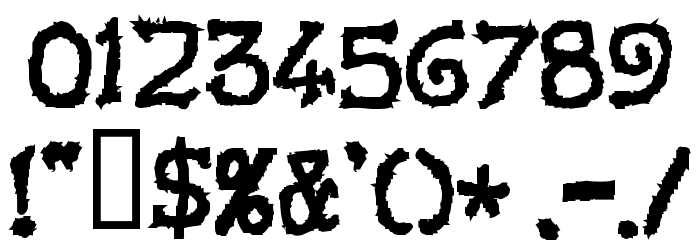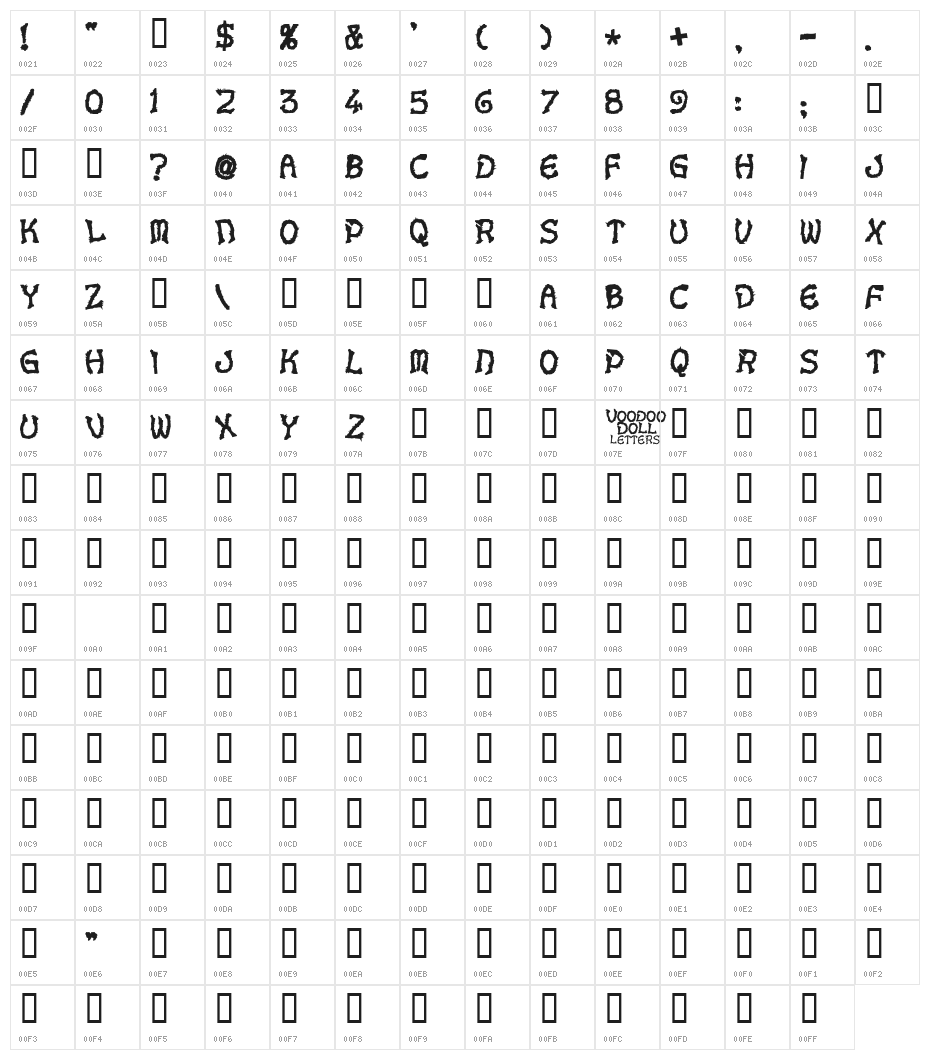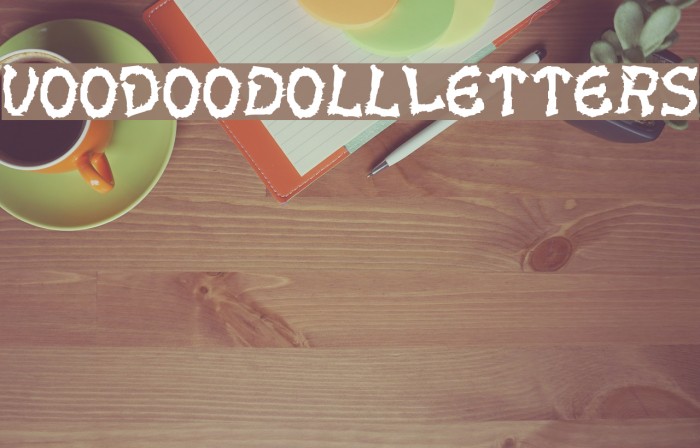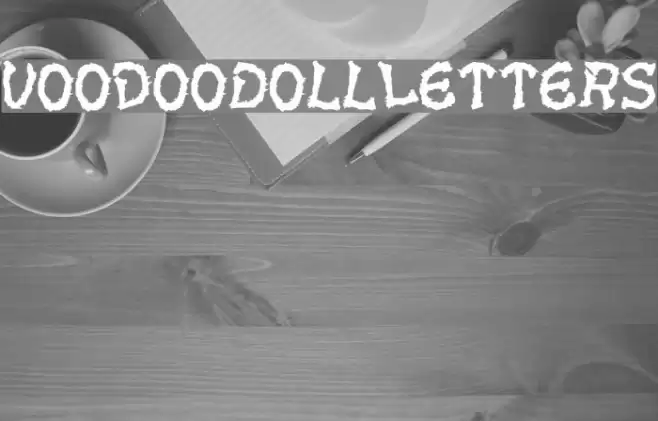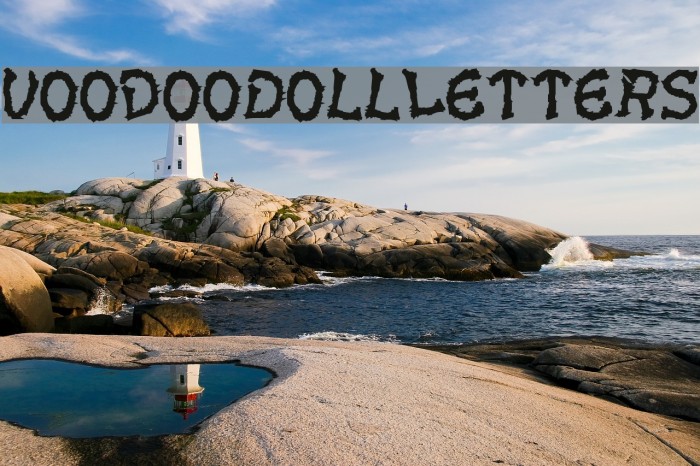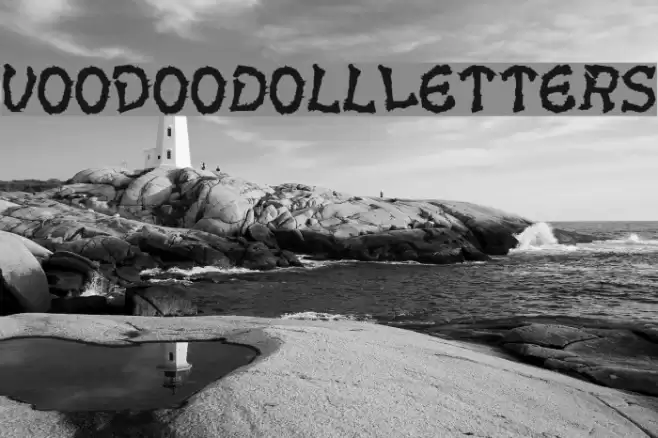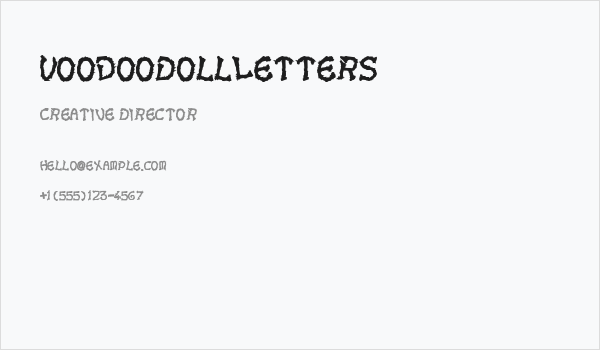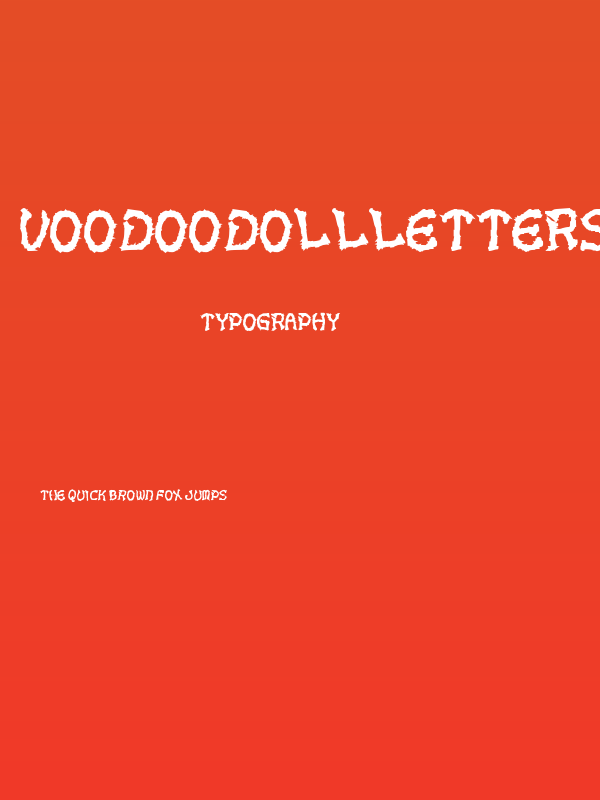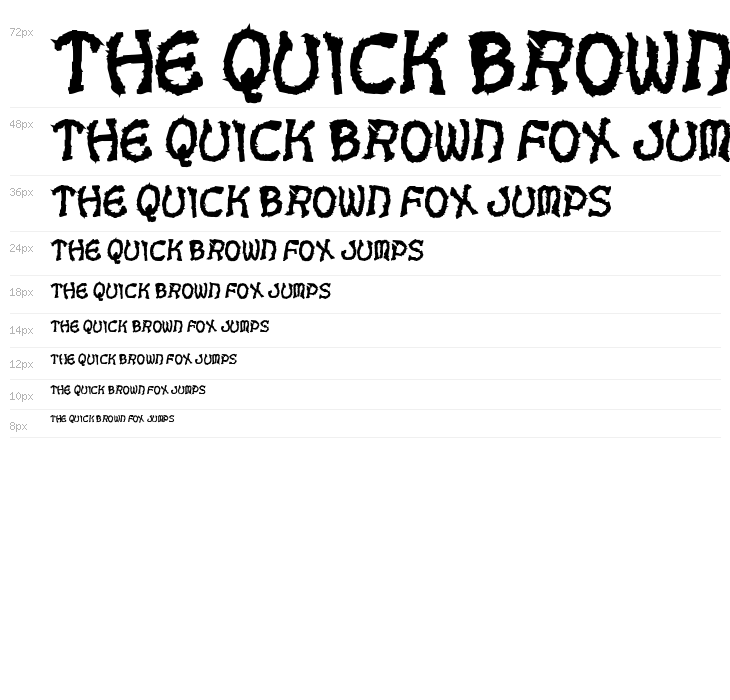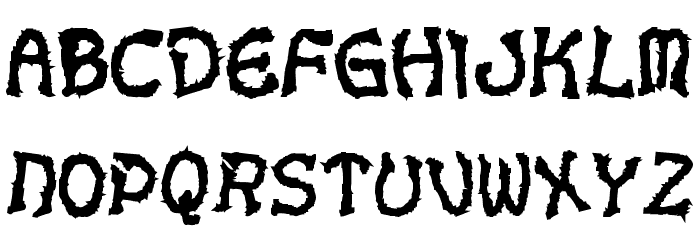
VoodooDollLetters Font
| Progetti proposti | Perfect for horror-themed designs, edgy posters, album covers, or any project needing a raw, organic touch. |